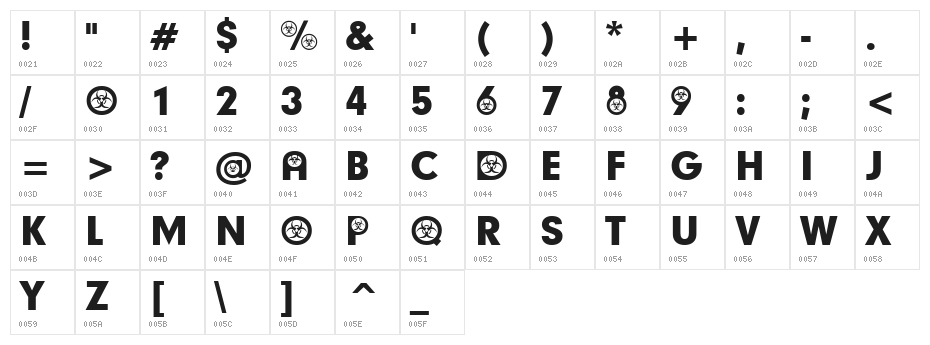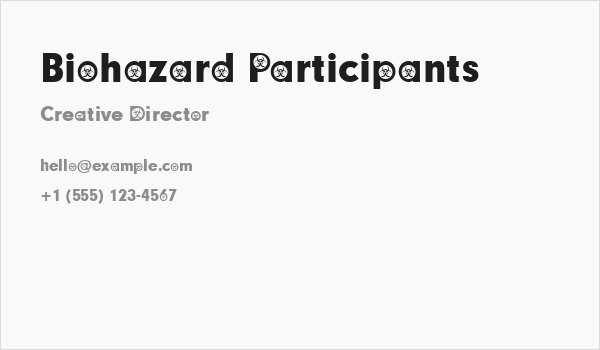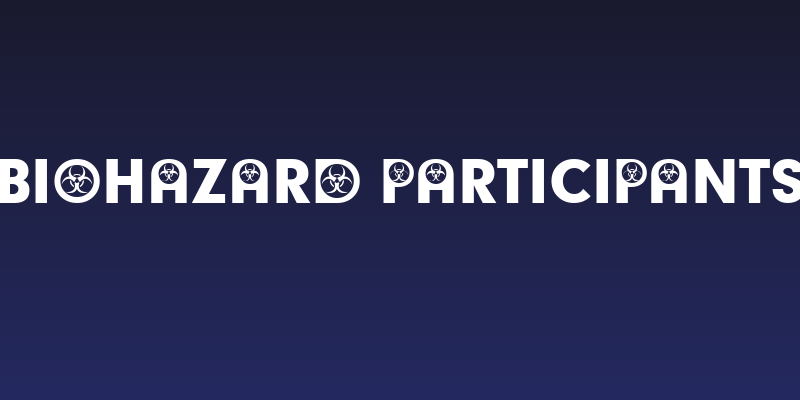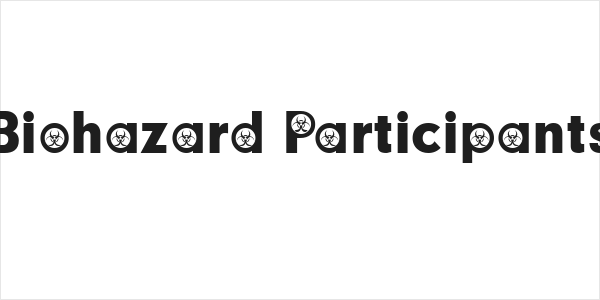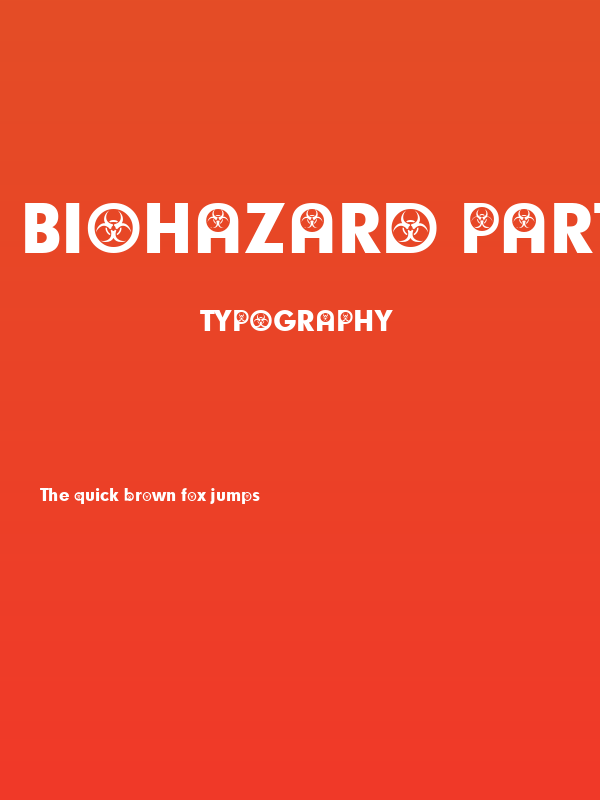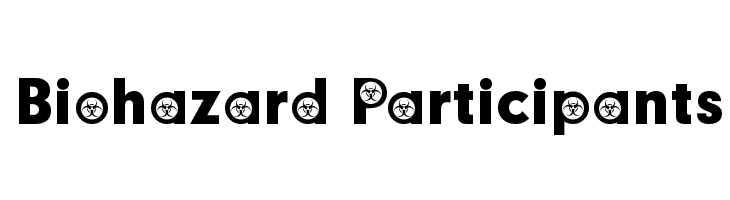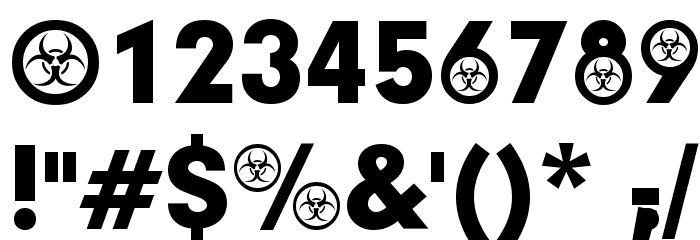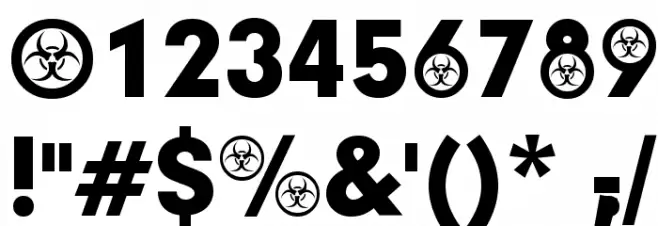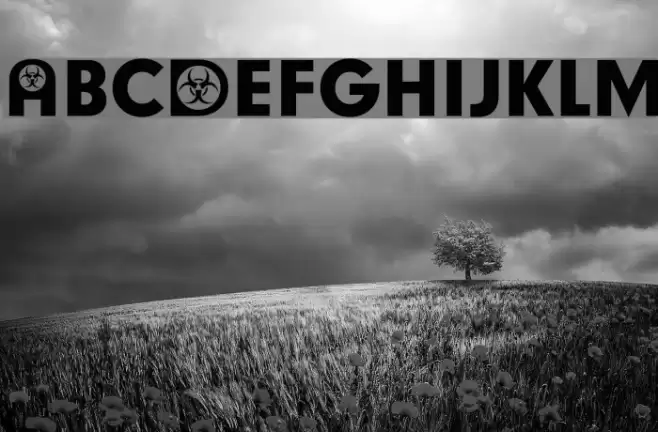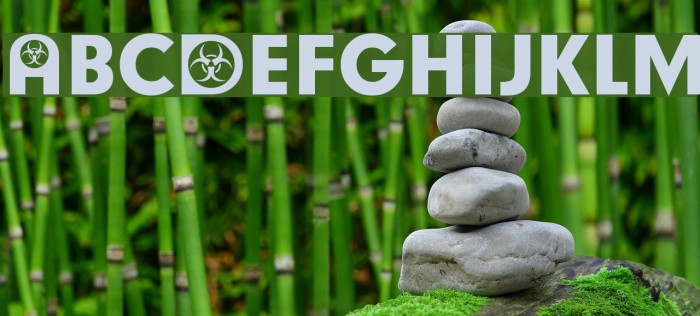
Biohazard Participants Font
| Vorgeschlagene Projekte | Ideal for projects requiring a bold statement, such as posters, album covers, or branding for edgy or alternative products. |